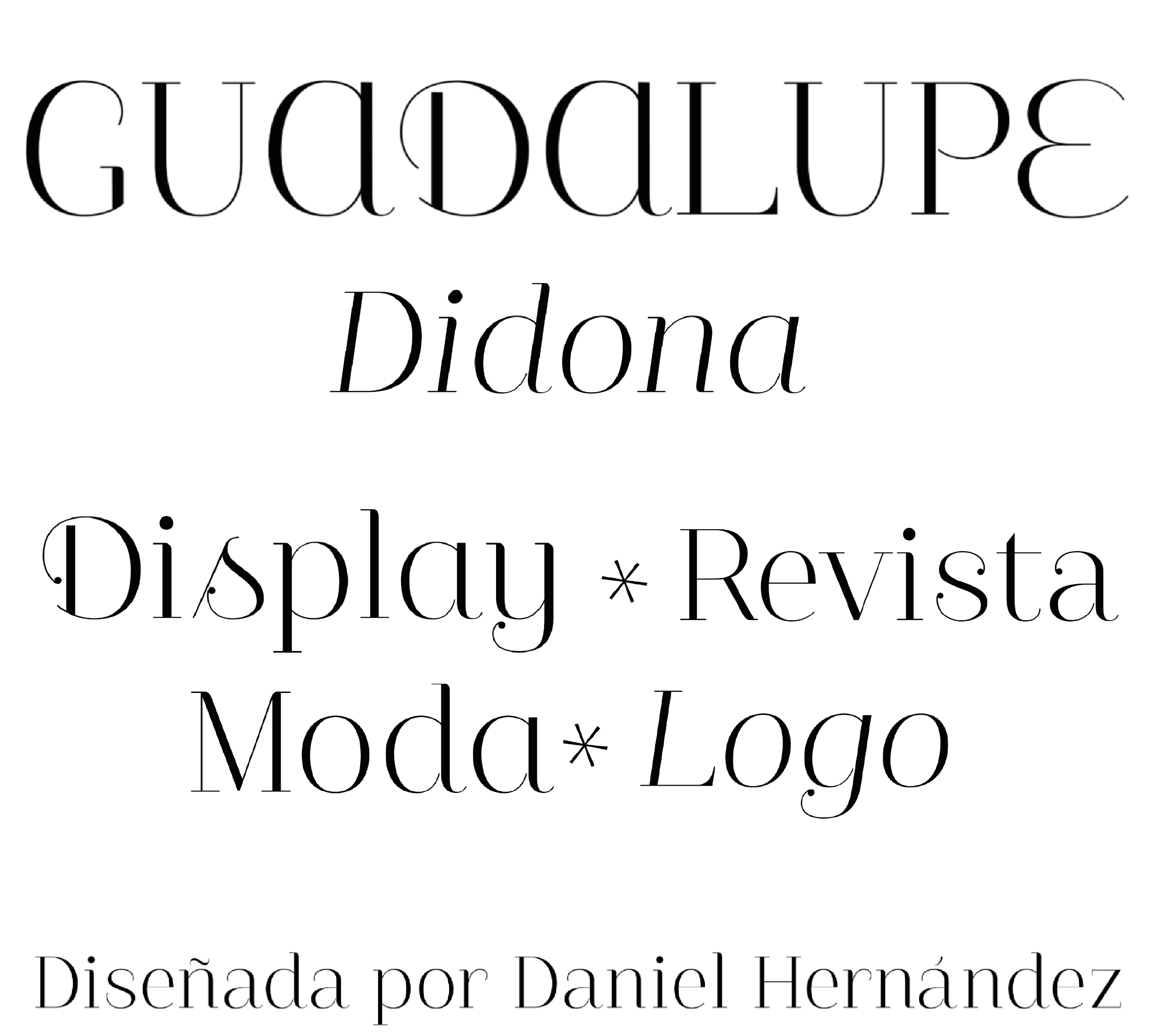
| Descripción | Guadalupe -de la familia de las clásicas Didots- es una fuente de alto rendimiento con un gran conjunto de alternancias y bastoncillos y detalles cuidadosamente refinados. Especialmente indicada para revistas de moda, logotipos y contextos de lujo con una gama de dos versiones terminales diferentes; Regular -una tipografía romana clásica- y Gota, mucho más expresiva para la composición de palabras. |
| Familia(s) | Guadalupe Essential, Guadalupe Essential Italic, Guadalupe Essential Gota, Guadalupe Essential Gota Italic, Guadalupe Pro, Guadalupe Pro Italic, Guadalupe Pro Gota, Guadalupe Pro Gota Italic |
| Estilos | 8 |